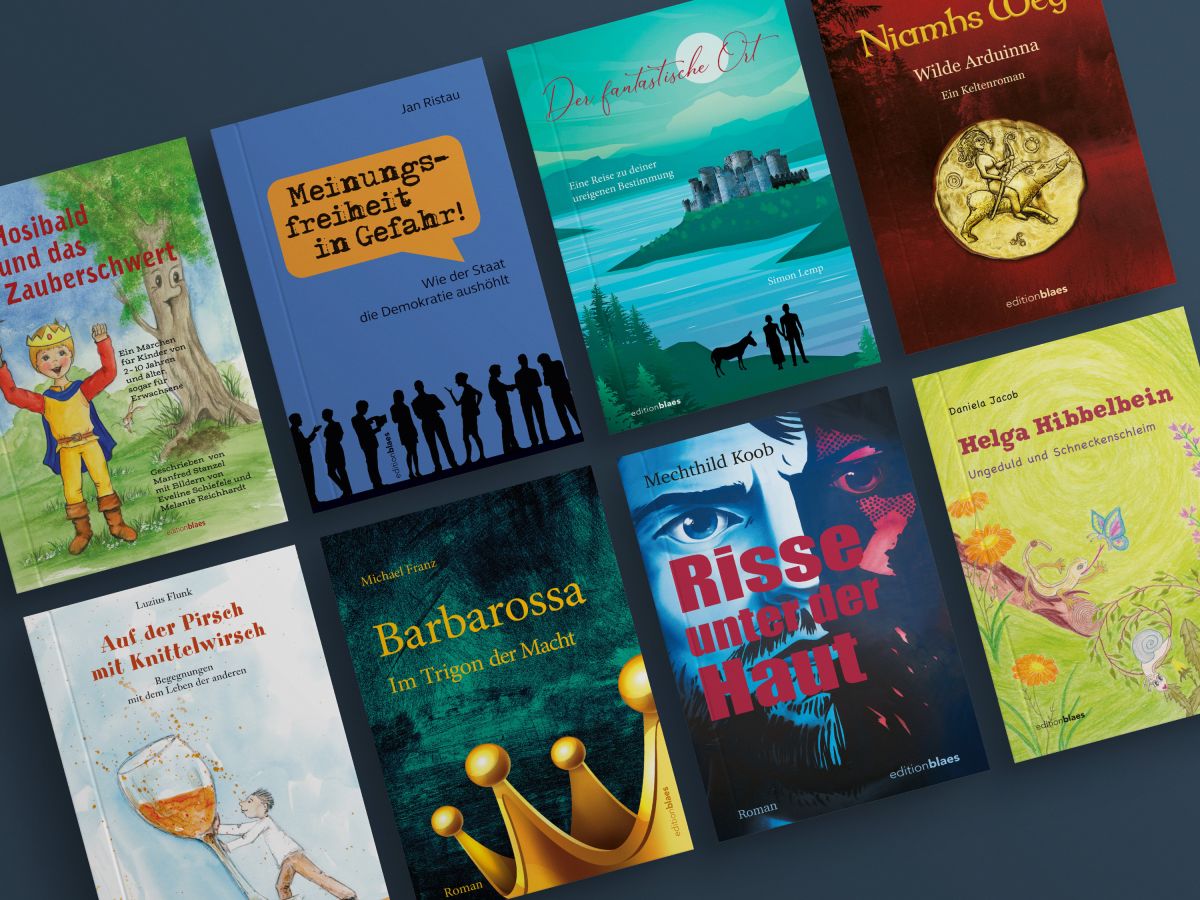
Warum Typografie unterschätzt wird - und professioneller Buchsatz so wichtig ist
Die Relevanz von einem guten Buchsatz wird von vielen Autoren unterschätzt. Das sieht man besonders bei Büchern von Selfpublishern, die mit WORD ihren Buchinhalt setzen.
Schondorf/Ammersee, 14. Januar 2026 - Typografie gehört zu den am meisten unterschätzten Faktoren bei der Buchproduktion. Oft wird sie erst dann wahrgenommen, wenn sie schlecht gemacht ist: holpriger Lesefluss, schlechte oder gar keine Silbentrennung, unruhige Seiten, ermüdendes oder schlecht lesbares Schriftbild. Dabei entscheidet professioneller Buchsatz maßgeblich darüber, ob ein Text gern gelesen wird - oder nicht.
Edition Blaes, geführt von Renate Blaes, setzt genau hier an. Mit über 30 Jahren Erfahrung im professionellen Buchsatz zeigt sie, dass Typografie weit mehr ist als Geschmackssache oder technisches Beiwerk. Sorgfältiger Erstzeileneinzug, saubere Silbentrennung und die Vermeidung von Hurenkindern sorgen für ein ruhiges, lesefreundliches Schriftbild.
Häufig unterschätzter Aspekt ist die Wahl der Schriftart. Groteskschriften wirken modern, eignen sich für Romane und umfangreiche Fließtexte weniger gut. Gezielt ausgewählte Serifenschriften sind meist die bessere Wahl. Doch auch innerhalb dieser Gruppe gibt es erhebliche Unterschiede, die Lesefluss und Charakter eines Buches maßgeblich beeinflussen. Diese Feinheiten entscheiden darüber, ob Lesen als angenehm oder anstrengend empfunden wird.
"Gute Typografie fällt nicht auf - schlechte hingegen sehr", erklärt Renate Blaes. "Gerade deshalb wird ihre Bedeutung häufig unterschätzt. Dabei ist sie entscheidend für die Qualität und Wertigkeit eines Buches."
Edition Blaes arbeitet mit Autoren und Selfpublishern zusammen und entwickelt individuelle Lösungen für jede Art von Publikation. Von Kinderbüchern, über Romane bis hin zu Sach- und Kochbuch Das Ergebnis sind Bücher, bei denen Typografie nicht dominiert, sondern dezent, aber wirksam den Buchinhalt präsentiert.